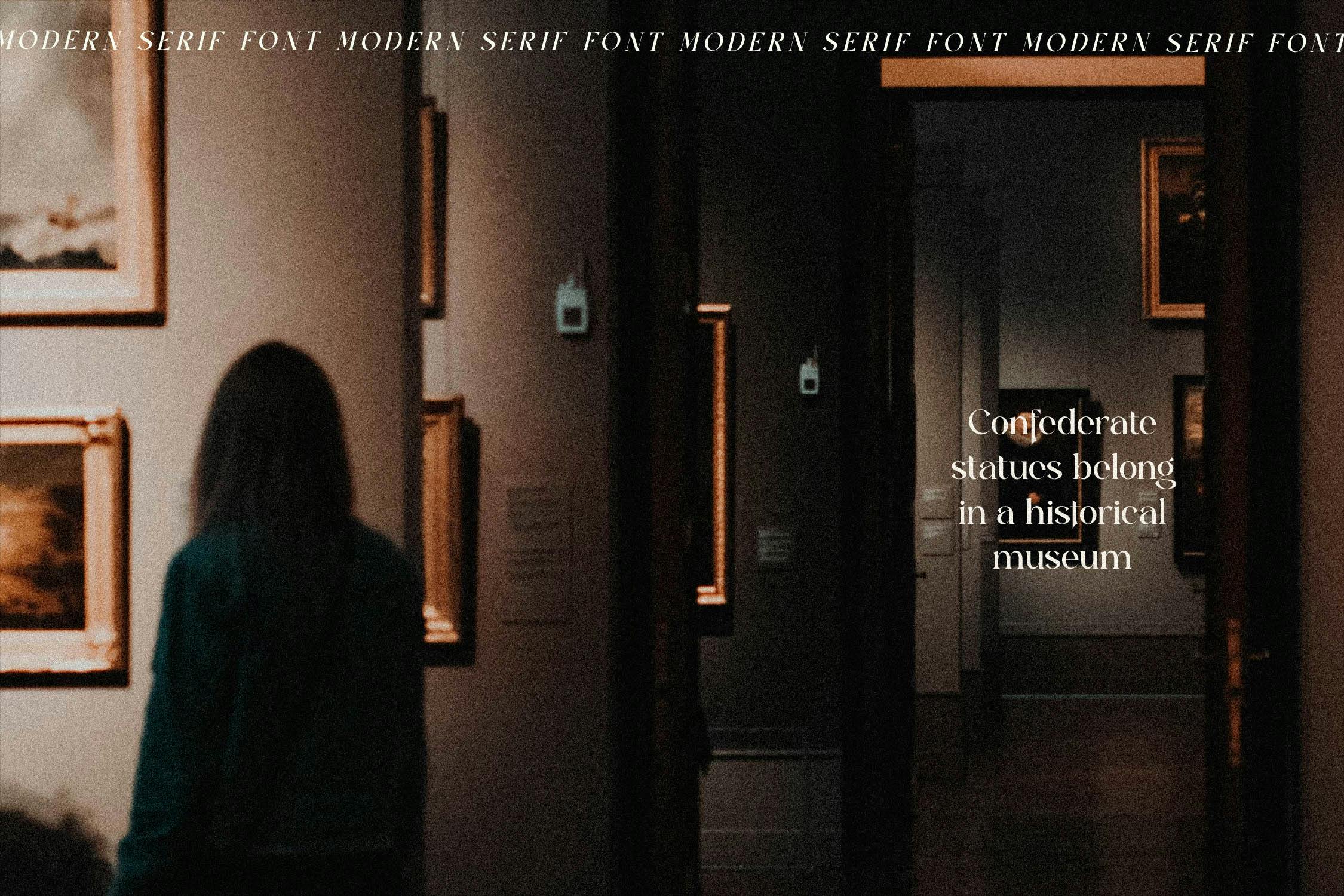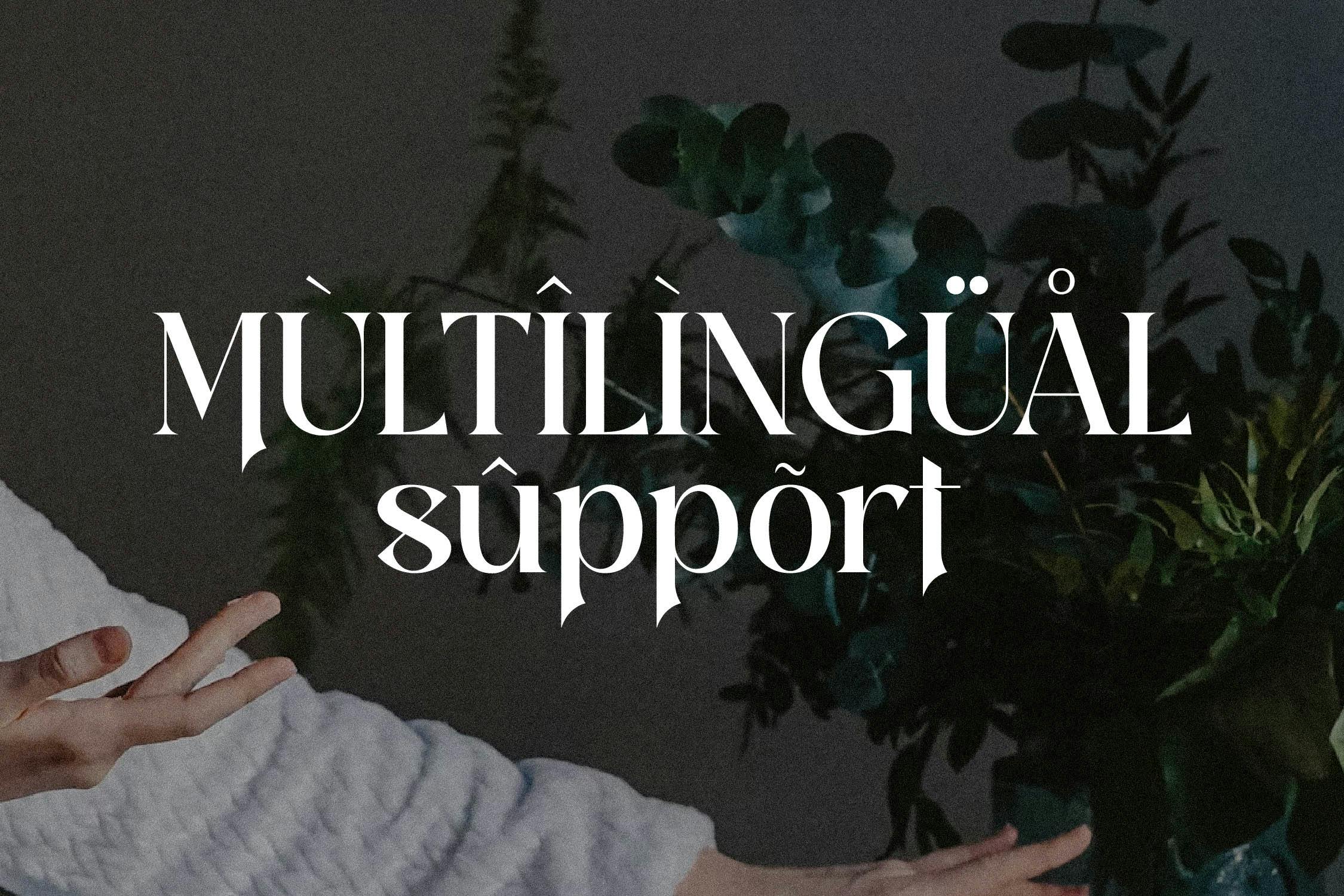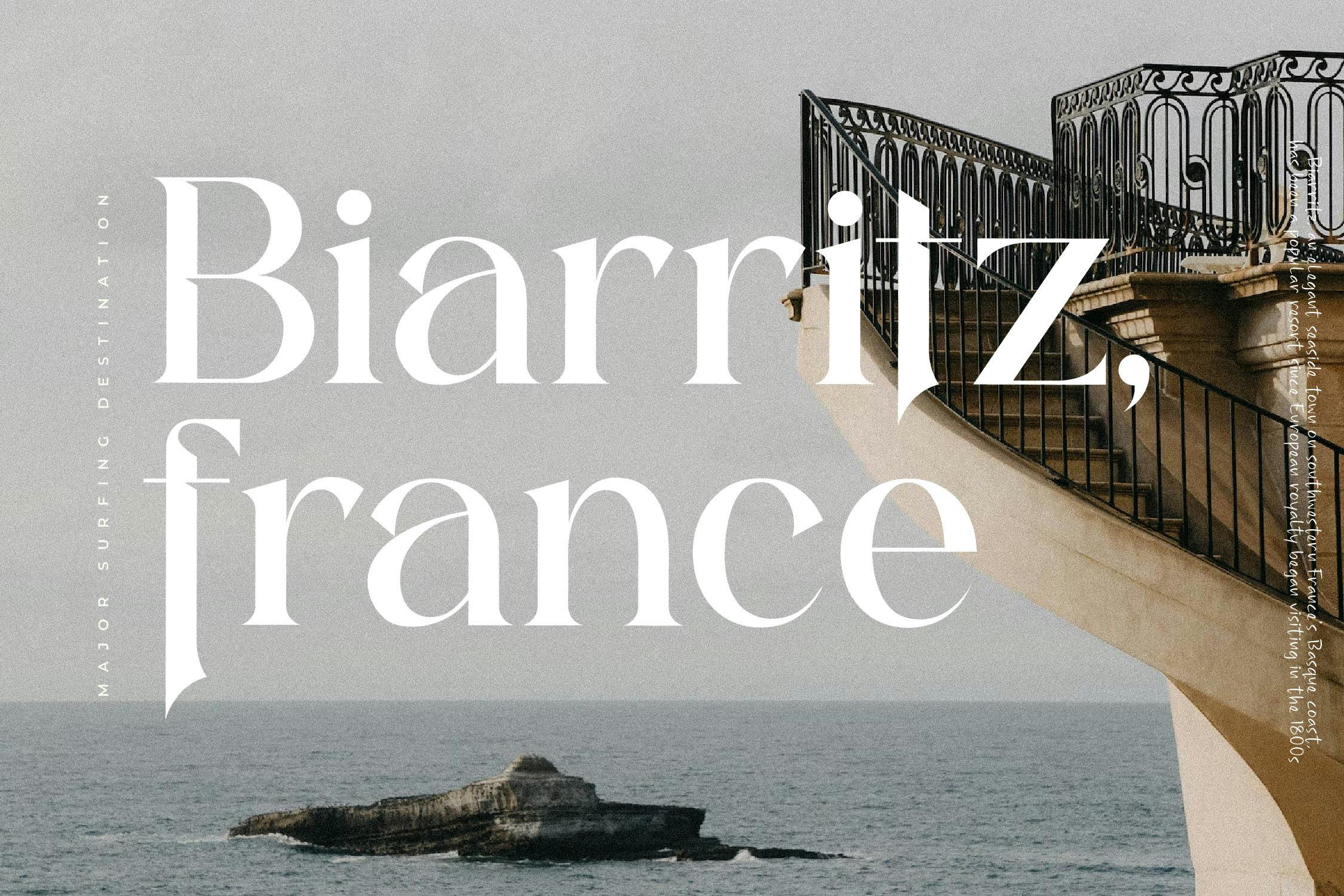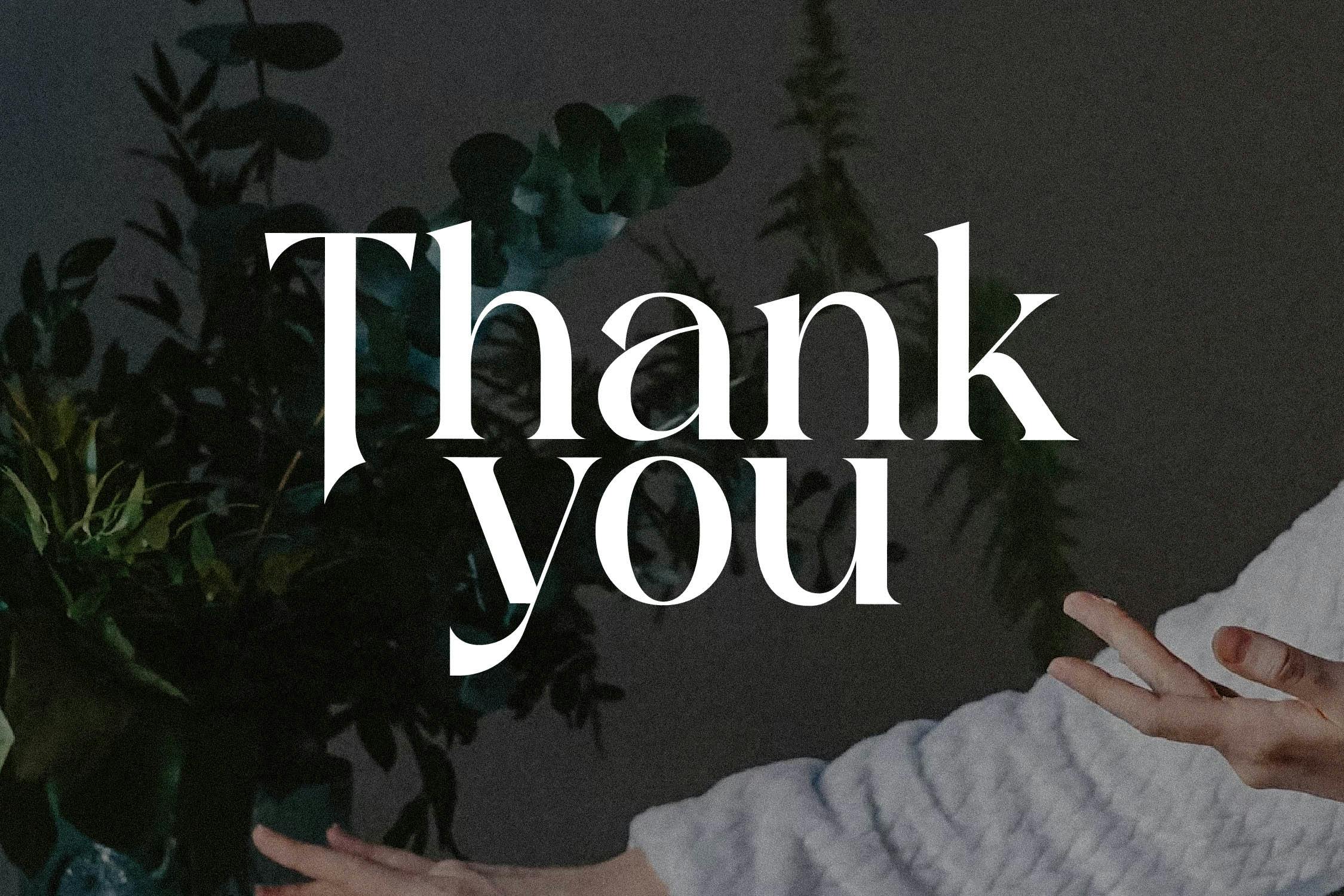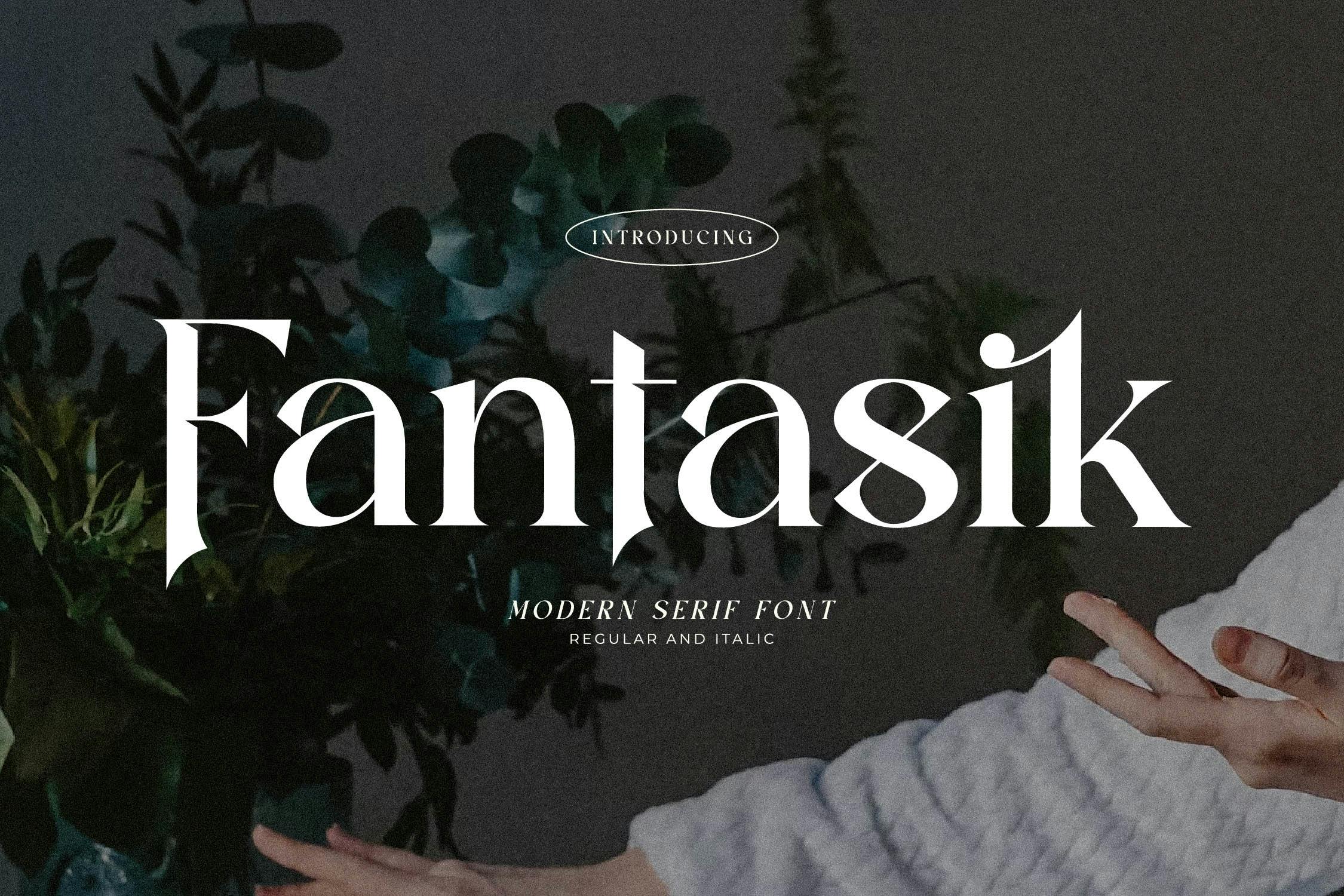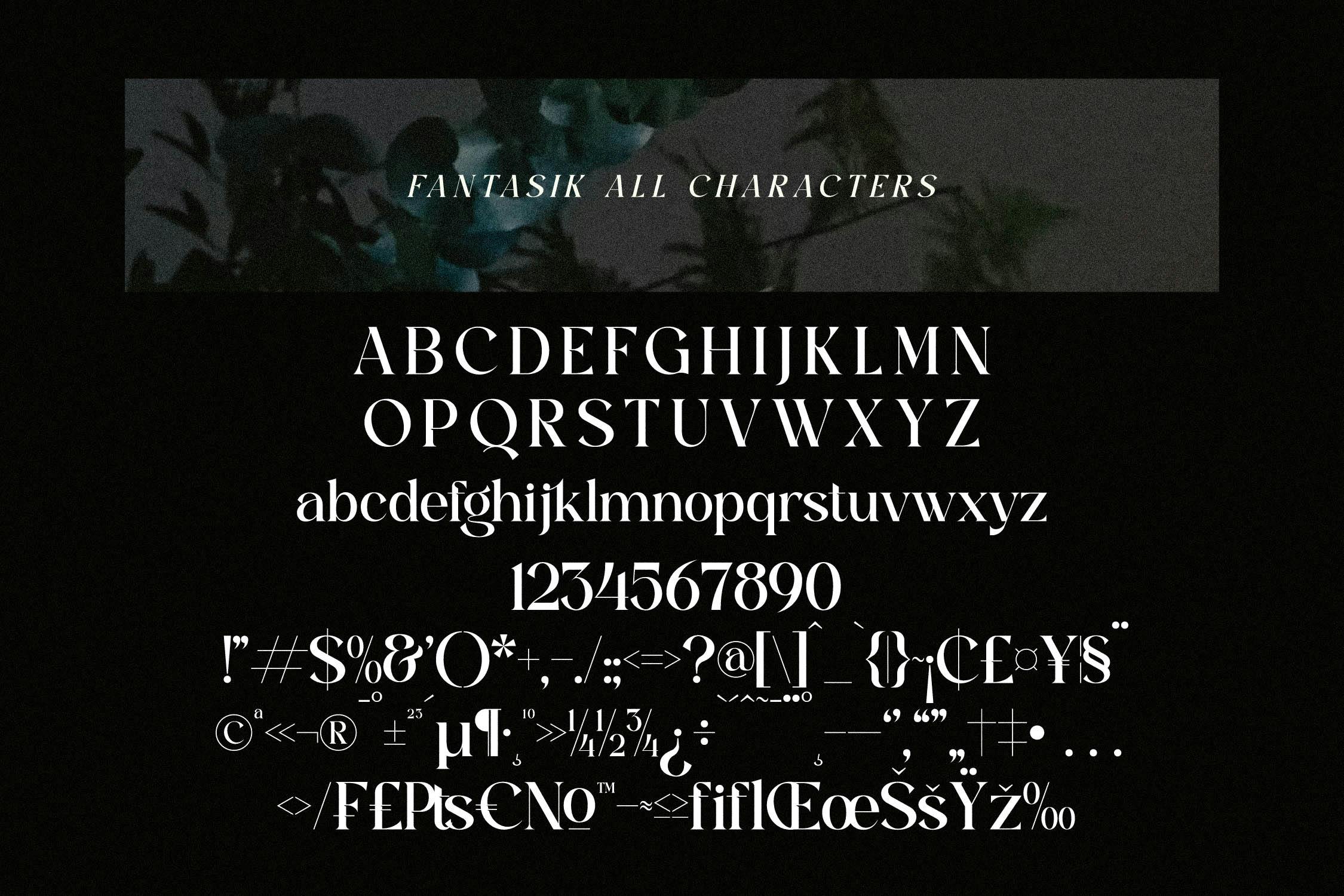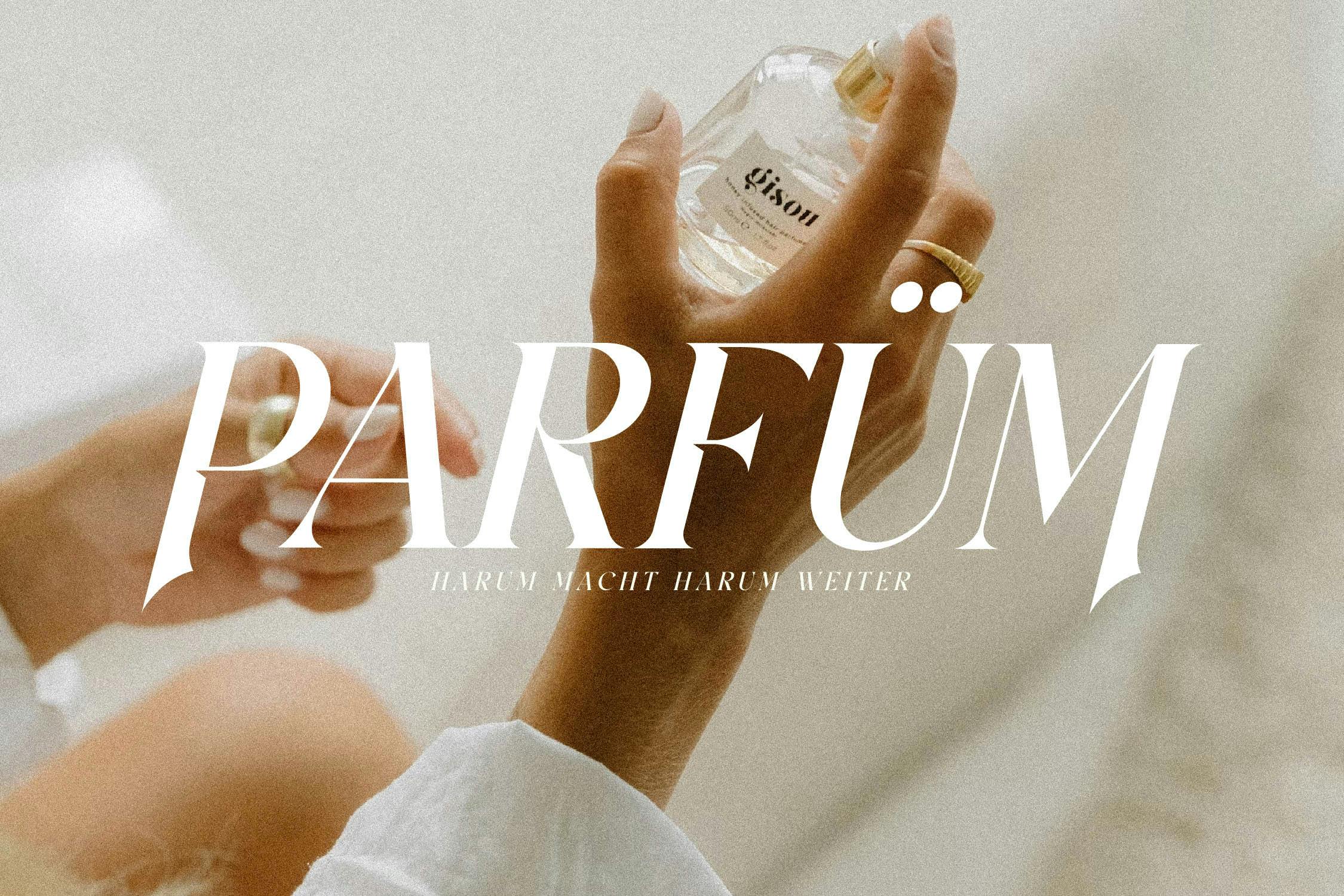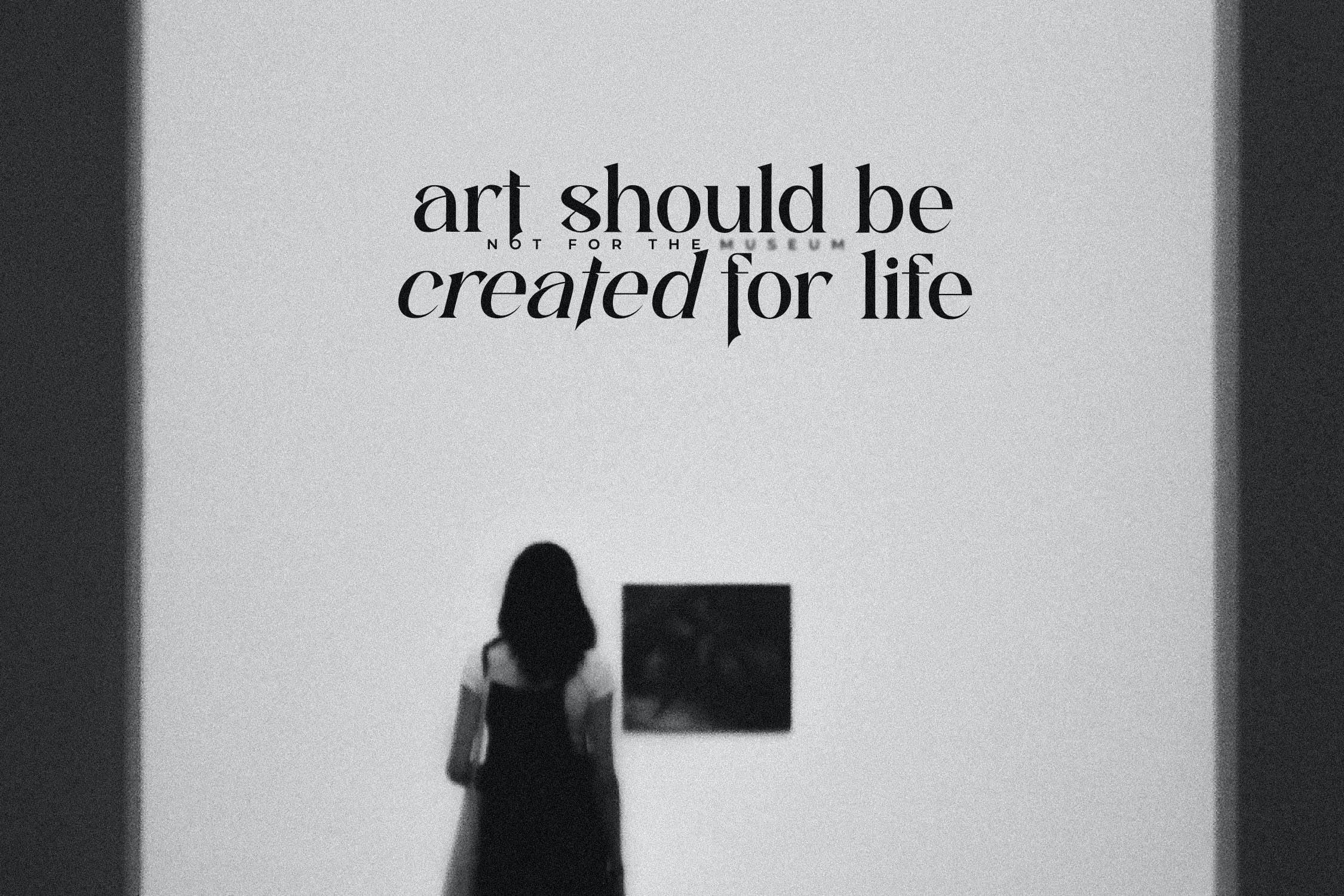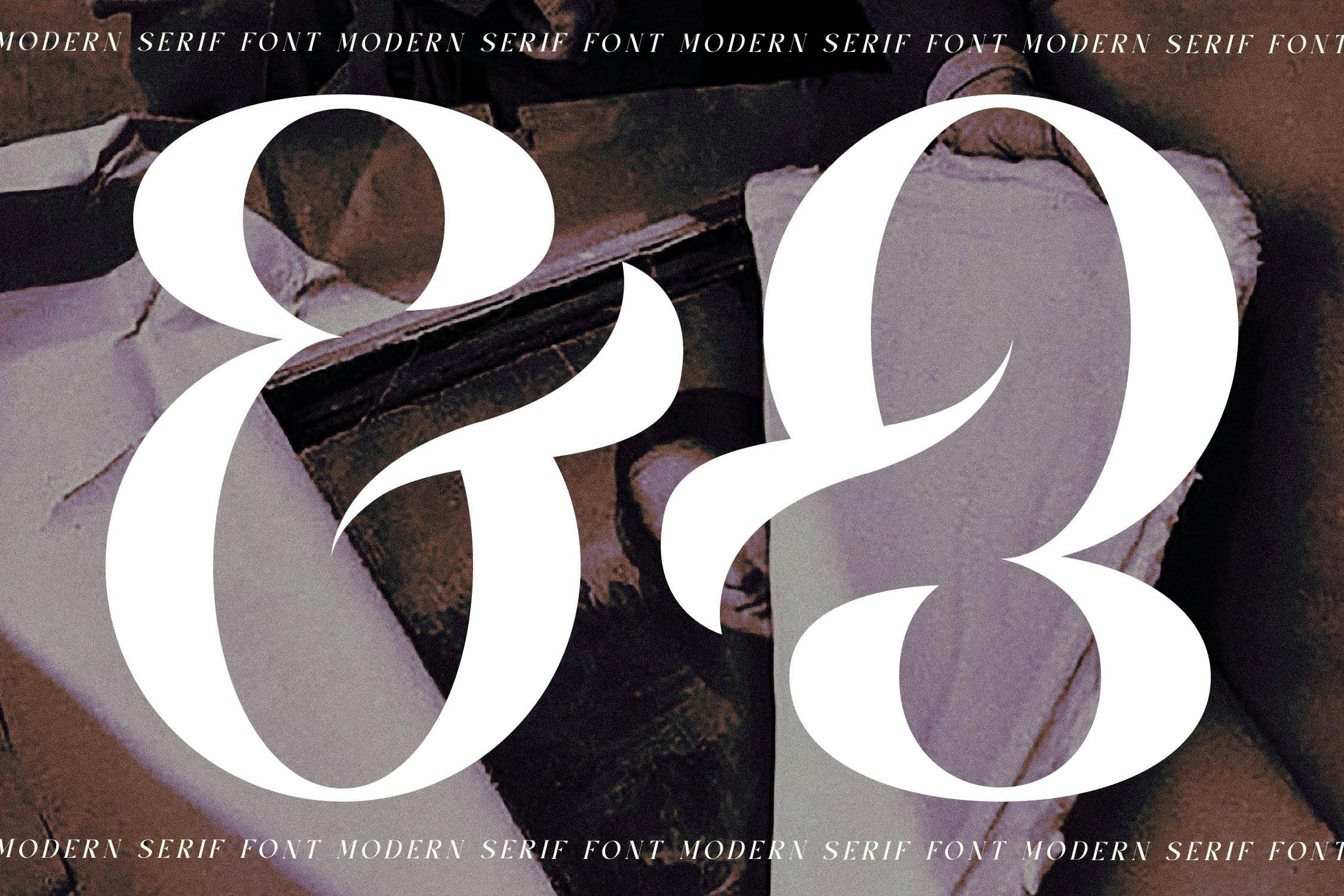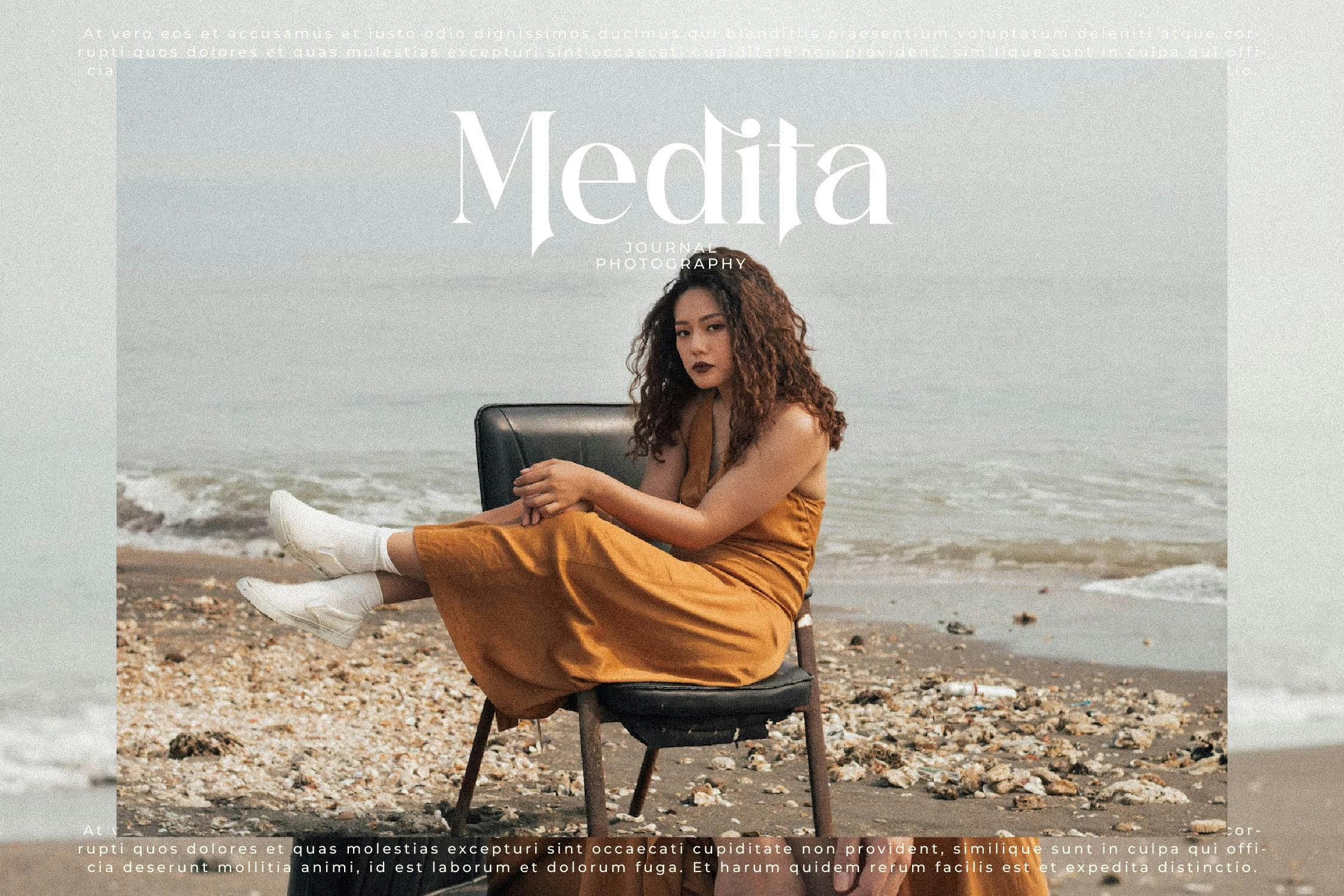
دانلود فونت سرسخت مدرن Fantasik
Fantasik Modern Serif Font
فونت سرسخت مدرن Fantasik، انتخابی عالی برای پروژه‌های خلاقانه شما.
این فونت برای طراحی پوسترها، پست‌های شبکه‌های اجتماعی، برندینگ و پروژه‌های شخصی بسیار مناسب است.